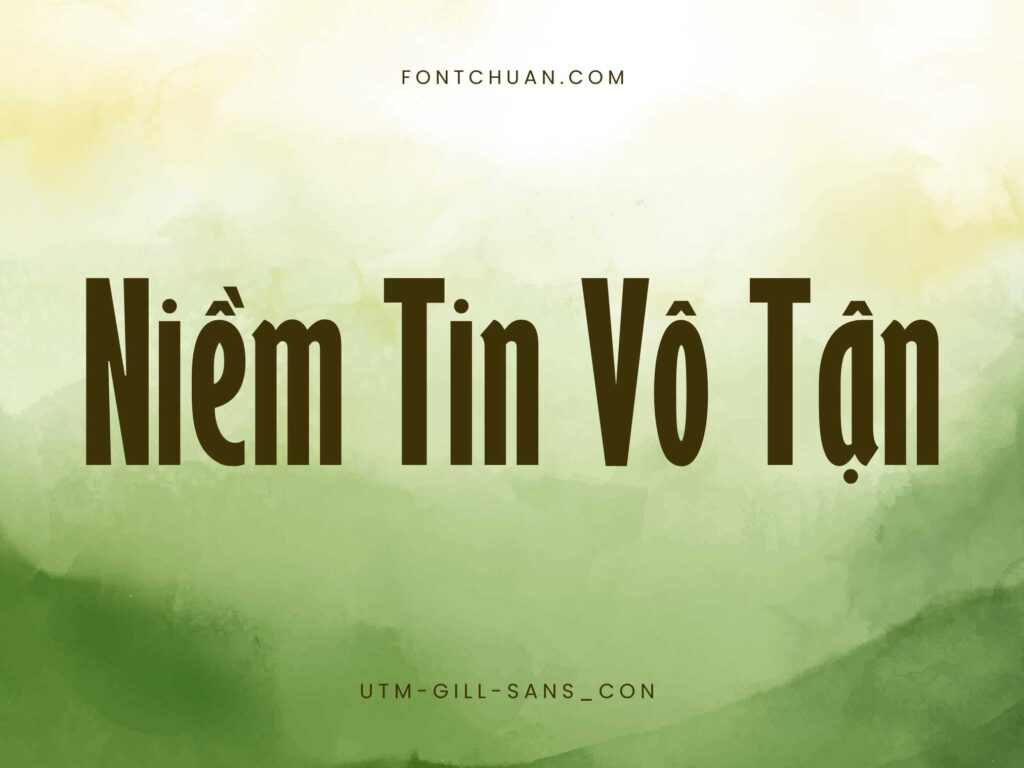
Gill Sans là một kiểu chữ sans-serif nhân văn được thiết kế bởi Eric Gill và được phát hành bởi chi nhánh Anh của Monotype từ năm 1928. Kiểu chữ này được lấy cảm hứng từ phông chữ Johnston của Edward Johnston, được sử dụng trong hệ thống tàu điện ngầm London. Gill Sans nhanh chóng trở thành một trong những kiểu chữ phổ biến nhất ở Anh, được sử dụng rộng rãi trong các biển báo, tài liệu và thiết kế đồ họa. Phiên bản UTM Gill Sans đã được Việt hóa bởi Thiên Minh, hỗ trợ tiếng Việt cùng hơn 200 ngôn ngữ khác, mở rộng khả năng ứng dụng trong nhiều lĩnh vực thiết kế. Thành viên của Font Chuẩn đã sưu tầm và chia sẻ phông chữ này nhằm đáp ứng nhu cầu của bạn đọc, cung cấp nguồn tham khảo chất lượng và ứng dụng thực tế vào các dự án thiết kế
Về đặc điểm thiết kế, Gill Sans có cấu trúc chữ cái dựa trên tỷ lệ cổ điển, với các đường nét sạch sẽ và độ dễ đọc cao. Phông chữ này phù hợp cho nhiều ứng dụng, bao gồm thiết kế logo, tiêu đề, văn bản nội dung và biển báo. Các ngành nghề như quảng cáo, giáo dục, công nghệ và thiết kế thương hiệu có thể tận dụng phông chữ này để tạo nên sự chuyên nghiệp và thu hút trong các sản phẩm thiết kế của mình